前回は、欧文フォントであるHama Mincho Itilicを例として、オプショナルなリガチャを呼び出す「任意の合字(dlig)」について紹介しました。日本語フォント場合、「任意の合字」は、「FAX」を「℻」に、「ミリバール」を「㍊」に、「株式会社」を「㍿」に置き換えるようなパターンのほかに、「JIS」を「〄」のような例もあります。そう言えば、話は完全に脱線しますが、JISマークは2004年に変更になったので、若い人はこの旧JISマークを見たことがないかもしれませんね。
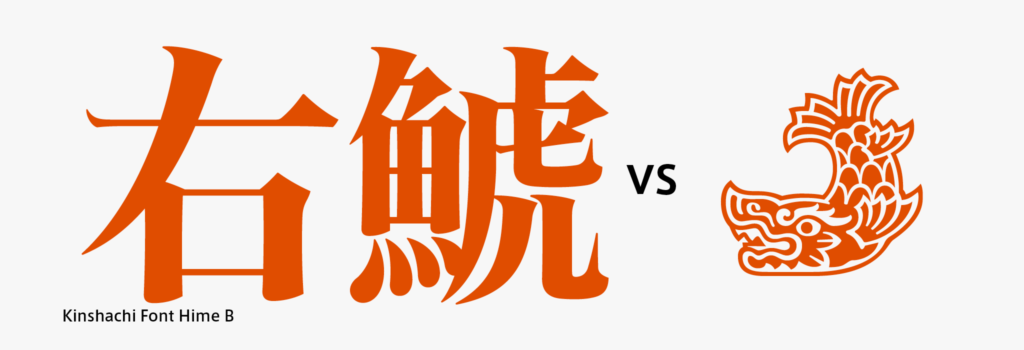
都市フォントプロジェクトのひとつである金シャチフォント 姫は、左右の金シャチマークを含んでいて、これを出力するために「任意の合字」を利用しています。「右鯱」「左鯱」から変換できます。
日本語フォントの「任意の合字」は、テキストの一部を選択して適用することを想定しているため、うっかりテキスト全体に適用したりすると、わけのわからないことになるので気をつけてください(OpenTypeフォントあるあるのひとつです)。